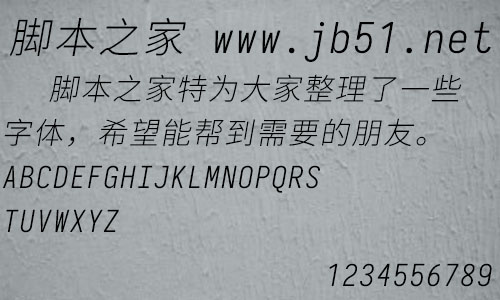
等距更紗黑體是更紗黑體中適合代碼編輯、終端的優(yōu)秀等寬字體,本文中帶來的則是等距更紗黑體 SC LightItalic,適合應(yīng)用于藝術(shù)設(shè)計、平面宣傳設(shè)計、網(wǎng)頁設(shè)計,書法字帖等領(lǐng)域,需要的朋友可以前來本站下載。
等距更紗黑體(sarasa-mono),由Iosevka和思源黑體組合起來的優(yōu)秀等寬字體,是更紗黑體其中的一款,有著獨(dú)特的“科技”風(fēng)味,很適合在代碼編輯、終端以及需要一些科技元素的平面設(shè)計里使用。